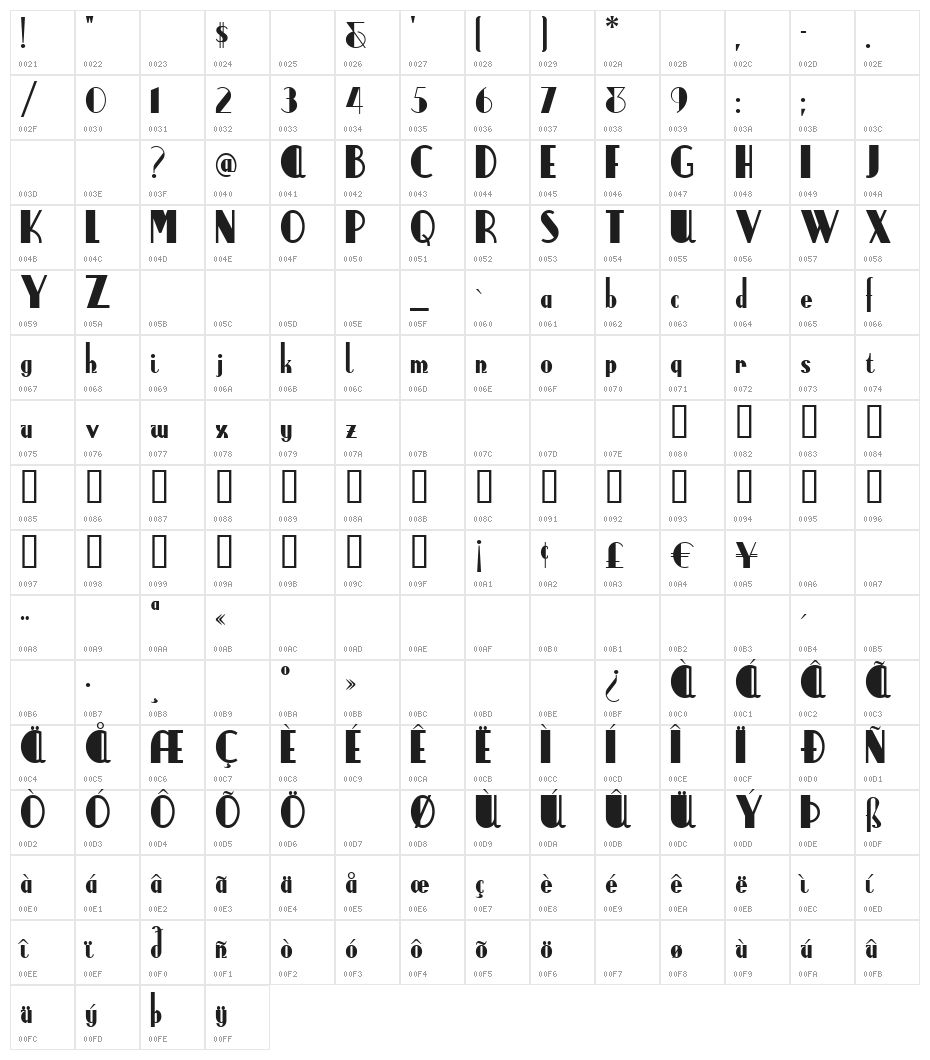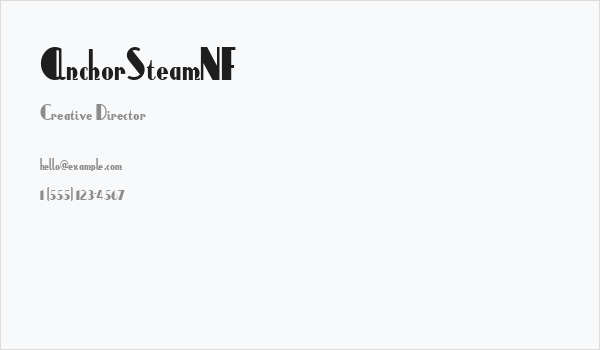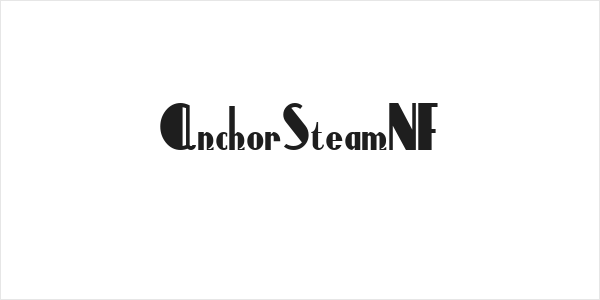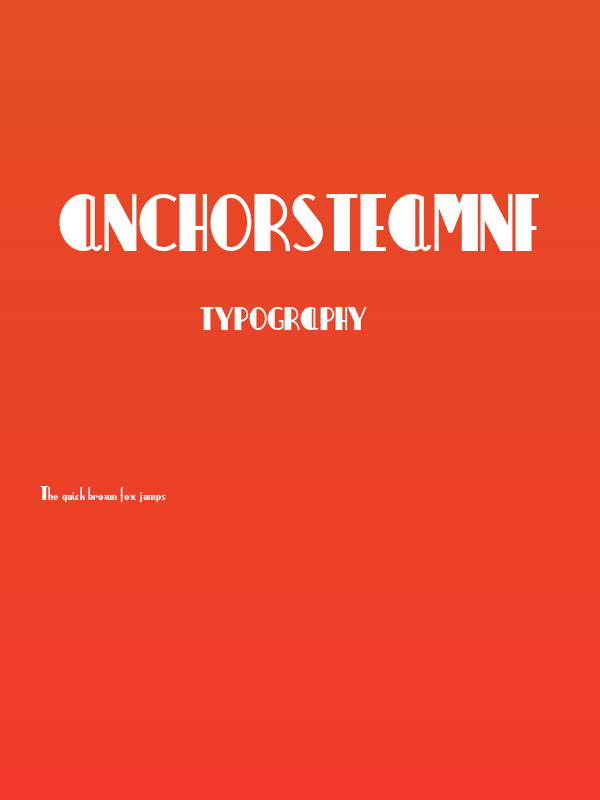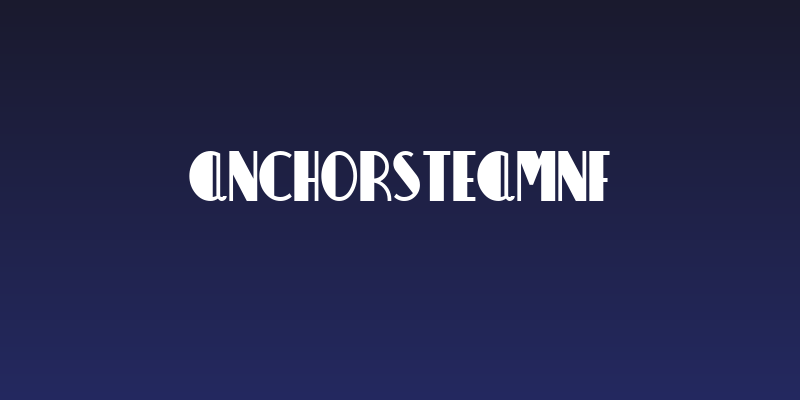
AnchorSteamNF Font
| Kategorien | Decorative |
| Gesamtstil | Vintage |
| Vorgeschlagene Projekte | Ideal for branding, poster design, packaging, and any project requiring a vintage or retro aesthetic. |